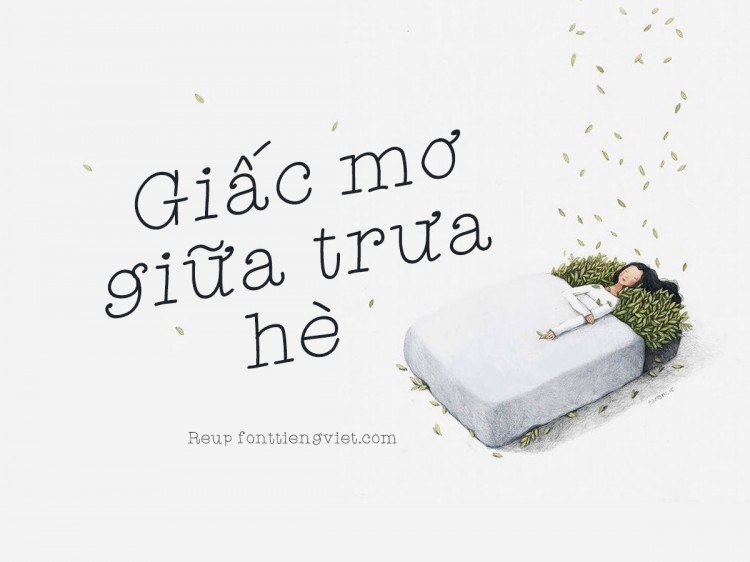
Giới thiệu về Font việt hóa LNTH limetart trong thiết kế đồ họa
Trong thế giới sáng tạo, việc lựa chọn một Font Chữ phù hợp đóng vai trò quan trọng giúp truyền tải thông điệp một cách hiệu quả. Font việt hóa LNTH limetart là một bộ font mang phong cách hiện đại, trẻ trung và đầy tính nghệ thuật. Được thiết kế với những đường nét mềm mại nhưng không kém phần phá cách, bộ font này đã trở thành lựa chọn ưu tiên của nhiều nhà thiết kế tại Việt Nam khi muốn tạo ra những sản phẩm hình ảnh ấn tượng và độc đáo cho học sinh, sinh viên.
Đặc điểm nổi bật của bộ Font việt hóa LNTH limetart
Sự linh hoạt trong ứng dụng thực tế
Font việt hóa LNTH limetart không chỉ dừng lại ở việc hỗ trợ đầy đủ bảng mã tiếng Việt mà còn mang lại sự cân đối hoàn hảo trong từng ký tự. Các khoảng cách giữa chữ cái được căn chỉnh tỉ mỉ, giúp văn bản trở nên dễ đọc và bắt mắt. Đây là bộ font lý tưởng để sử dụng trong các bài thuyết trình học đường, thiết kế bìa sách hoặc làm tiêu đề cho các video sáng tạo trên mạng xã hội hiện nay.
Tính thẩm mỹ và sự sáng tạo không giới hạn
Điểm mạnh của bộ font này nằm ở khả năng biến hóa đa dạng. Dù bạn đang thực hiện một poster sự kiện sôi động hay một thiệp mời nhẹ nhàng, bộ font vẫn giữ được cái “chất” riêng biệt. Sự kết hợp giữa nét thanh và nét đậm tạo nên một nhịp điệu thị giác thú vị, giúp người xem dễ dàng ghi nhớ nội dung mà bạn muốn truyền tải một cách tự nhiên nhất.